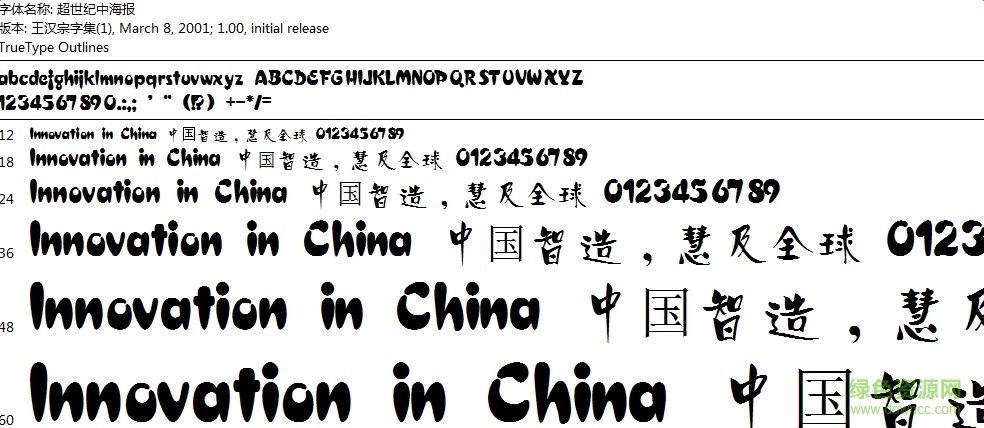
超世紀(jì)中海字體是一款極具中國(guó)古風(fēng)水墨風(fēng)格的精美字體。整個(gè)字體使用起來(lái)十分的舒服,視覺(jué)效果也是很不錯(cuò)的,它在傳統(tǒng)的字體風(fēng)格增加一些不同元素的藝術(shù)加載,喜歡的小伙伴們快來(lái)綠色資源網(wǎng)下載吧!
極富裝飾意趣。適用于書(shū)、報(bào)、雜志的各類標(biāo)題字和裝飾、宣傳用字。
筆劃纖細(xì),字體清秀工整,結(jié)構(gòu)均勻,印刷效果清晰明快,適用于報(bào)紙、雜志的正文。
精致、華貴、大氣、端莊,筆形富于變化,浪漫而又溫馨。宜作排版文章標(biāo)題,以及一切廣告用字。
字體神采俊俏,雄渾中流露天真稚拙,典雅中蘊(yùn)含時(shí)代風(fēng)采,靜中寓動(dòng)、穩(wěn)中求險(xiǎn)、巧拙相生、變化自然,結(jié)體嚴(yán)謹(jǐn),筆法古樸典雅,又